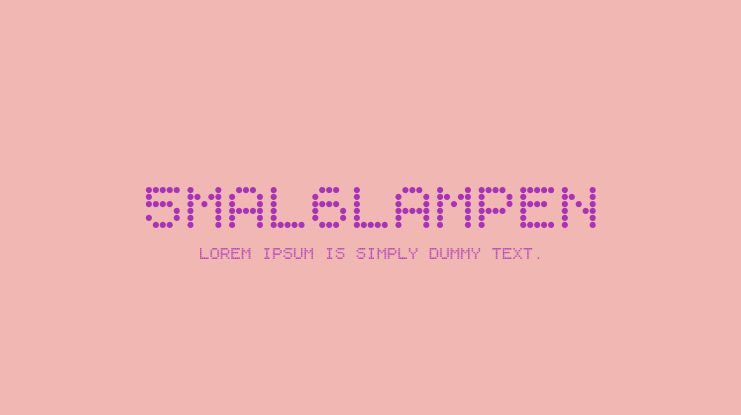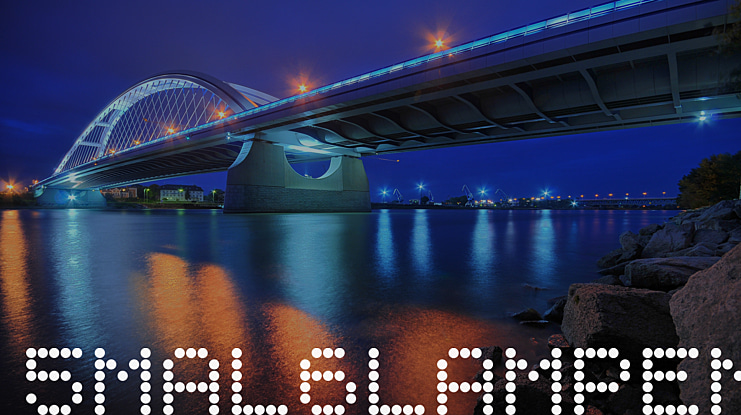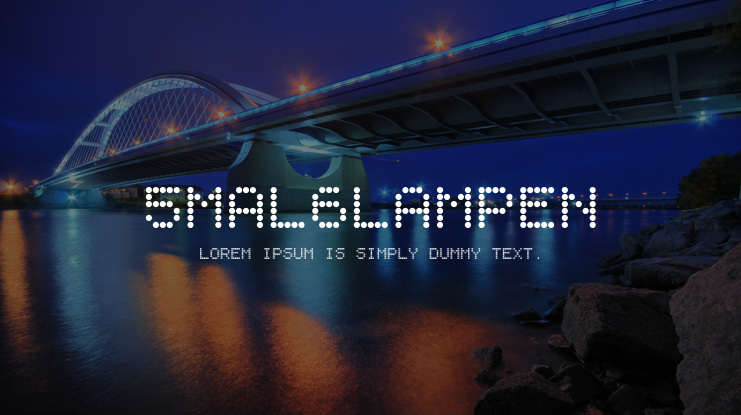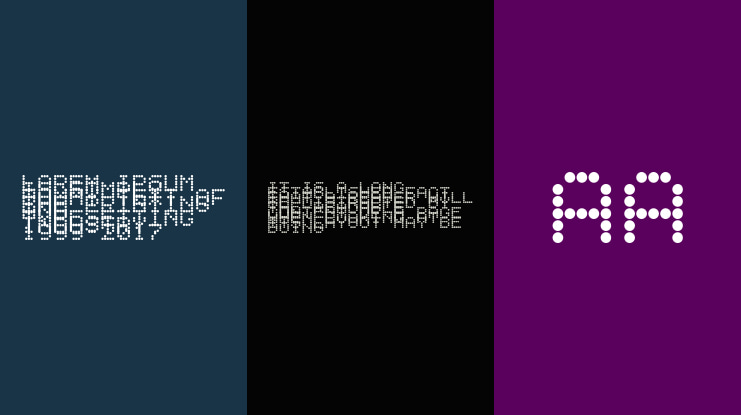
5mal6Lampen Font
Um 1970 verschwanden die rein manuell bedienten Spielstand-Anzeigen nach und nach aus den Stadien der oberen Spielklassen. Ersetzt wurden sie durch die ersten elektronischen Anzeigetafeln, die dann auch mehr informationen dem Zuschauer geben konnten. Noch waren es Glühlampen, welche die Buchstaben formten. Dies hier ist die kleine Schriftgröße, bei der jeweis eine Glühlampenreihen die Linien der Schrift formten, also mit 5 mal 6 Glühlampen auf der Fläche eines Buchstaben